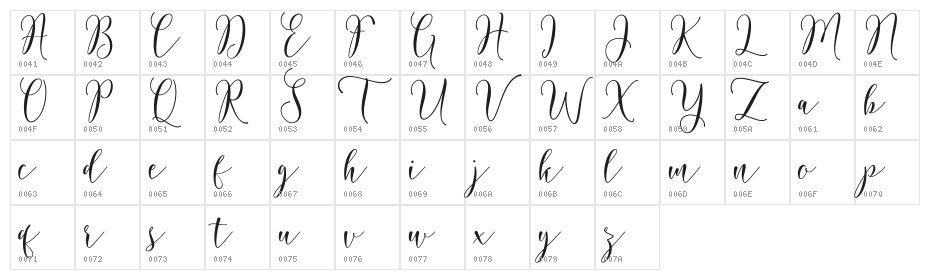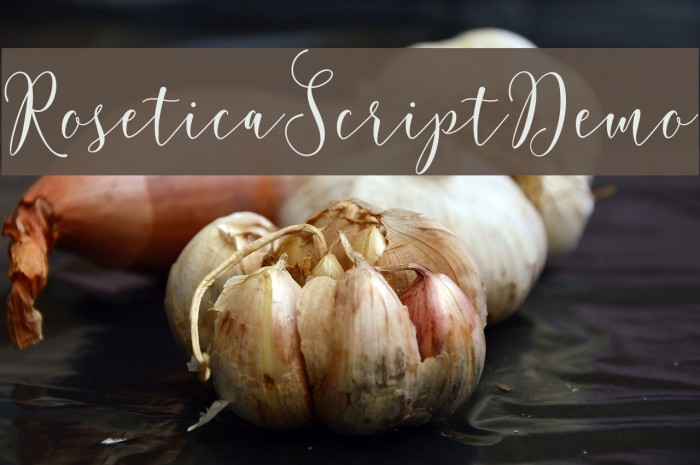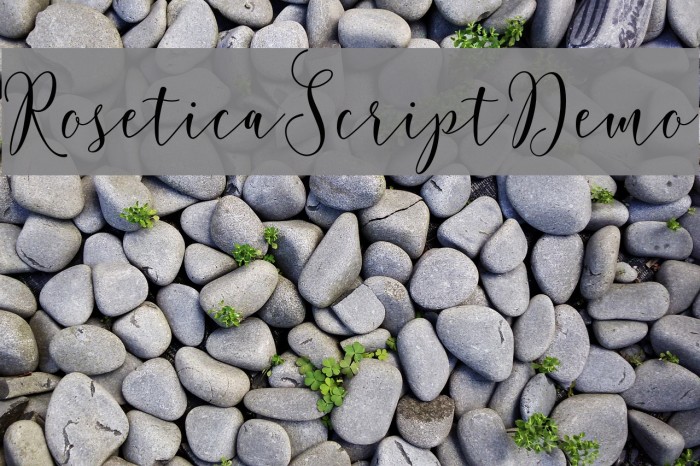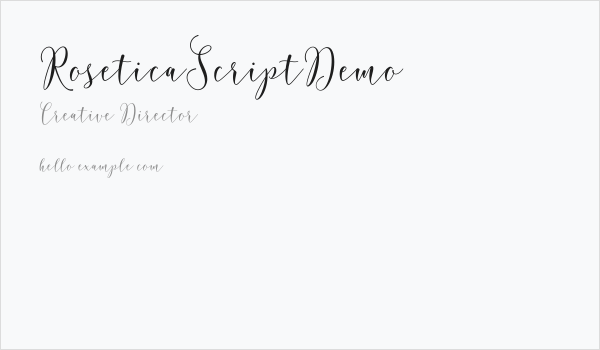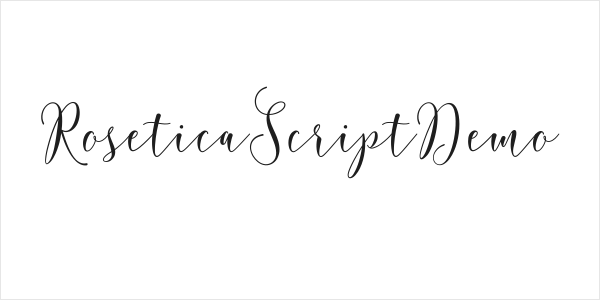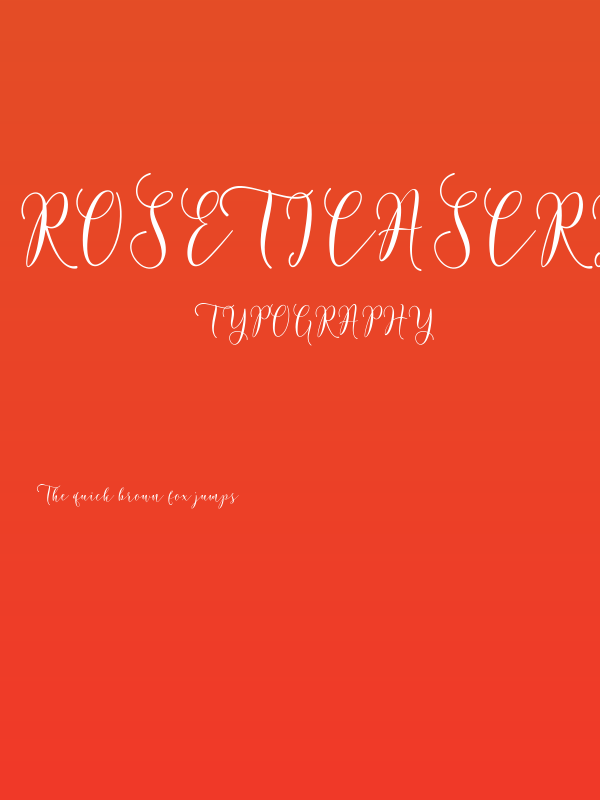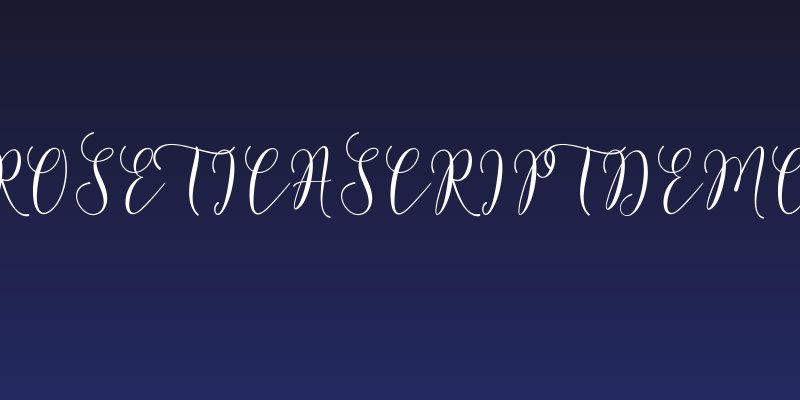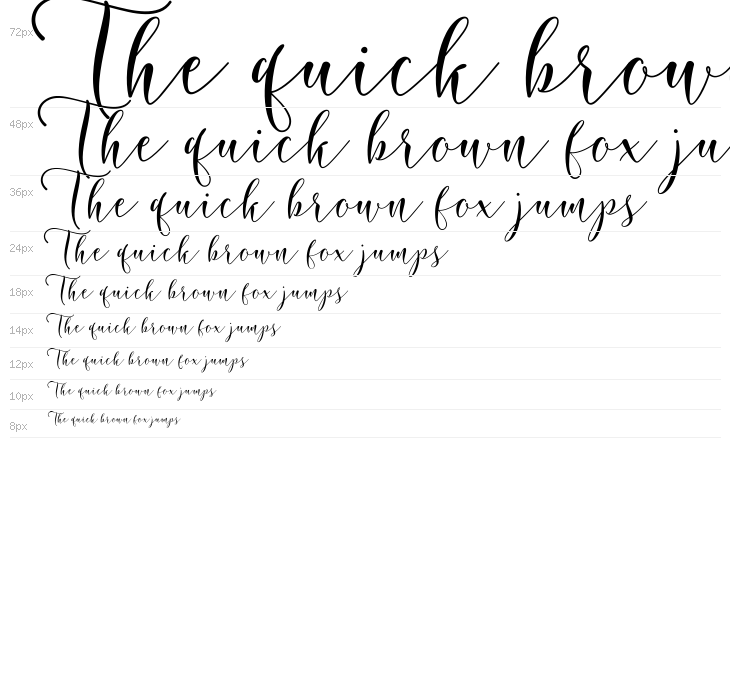
RoseticaScriptDemo Font
✎ Calligraphic
| Anwendungsfall | Logos, Invitations, Decorative text |
| Vorgeschlagene Projekte | Ideal for wedding invitations, elegant branding, greeting cards, and decorative quotes. |